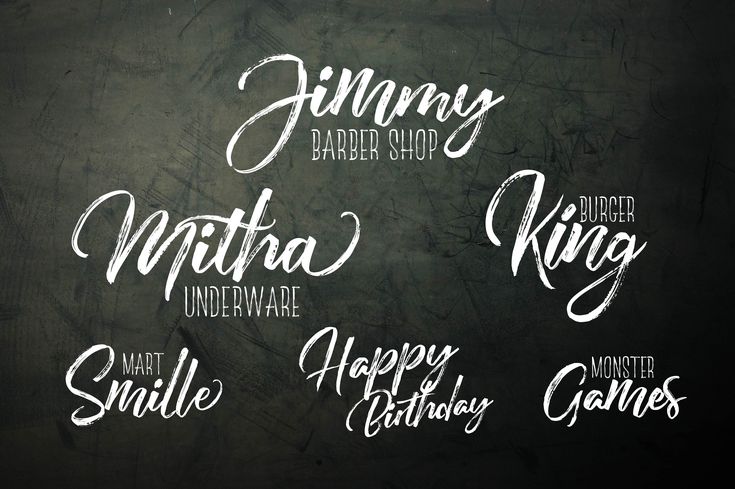
Подборка бесплатных русских рукописных шрифтов — Таня Захар на vc.ru
1. Шрифт Celestina скачать бесплатно
Отличный рукописный шрифт, он кажется довольно веселым и игривым, эта эмоция выражается благодаря разной высоте построения букв. Длинный текст читается довольно трудно, поэтому не используйте celestina шрифт кириллица в больших объёмах.Скачать шрифт Сelestina
2. Шрифт Brush font one скачать бесплатно
Бесплатный рукописный шрифт — Brush Font One созданный от руки и относится к классу шрифтов без засечек. Поддерживает латиницу и кириллицу. Довольно выразительный шрифт с угловатыми буквами. Подойдет на те случаи, когда нужно создать эффект написанного вручную. В целом — очень даже красивый шрифт для текста. Подходит для личного и коммерческого использования.Скачать шрифт Brush font one
3. Шрифт Elowen скачать бесплатно
Нежный, мягкий каллиграфических шрифт с толстой кистью .
Подойдет для рекламных компаний детских или женских брендов. Elowen Caps — Ваш отличный компаньон в тех случаях, когда нужен яркий заголовок. Поддерживает латиницу и кириллицу.Elowen русский шрифт скачать
4. Шрифт березки скачать бесплатно
Еще один легендарный шрифт от Миши Панфилова. Шрифт березки выделяется на фоне остальных благодаря вытянутым буквам, «нацарапанные» с легкой небрежностью и задиристостью, подойдут неформальному бизнесу — как на вывеске, так и в вебе. Настойчиво рекомендуем добавить его в свою рабочую папочку «шрифты для фотошопа». Поддерживает кириллицу. Березки шрифт скачать
5. Шрифт Tangak скачать бесплатно
В данном топе представлен шрифт «Tangak» не зря! Неформальный и уникальный шрифт для айдентики кафе и бара. Заголовка в книгах и прочей полиграфии. Шрифт поддерживает латиницу, кириллицу, цифры, знаки препинания и пунктуации, прописные и строчные буквы. Шрифт «Tangak» Вы можете скачать бесплатно в форматах EOT, OTF, SVG, TTF, WOFF, WOFF2.
6. Шрифт Gvozdi скачать бесплатно
Gvozdi шрифт — смотрится забавно на этой картинке, но автор не имел и другой посыл: если применять рукописный шрифт Гвозди в образовательных или художественных текстах, к примеру, о войне, читатели заметят эту небывалую «злость» и «агрессию». Наша редакция часто его использует в своих проектах и считает, что это очень красивый русский шрифт.Скачать рукописный шрифт Гвозди
7. Шрифт Kurica Lapoi скачать бесплатно
Тут-то и название красноречивое, говорит само за себя: корявый, как бы небрежный «Курица лапой» добавит юмора в ваш дизайн. Если не боитесь смеяться над собой, скачайте этот шрифт.Kurica Lapoi шрифт
8. Шрифт lemon tuesday скачать бесплатно
«Лимонный вторник» яркий и неординарный шрифт, его можно поставить в заголовке меню летнего кафе — он подчеркнет непринужденность и легкость обстановки. Но помните, что хотя скачущие буквы выглядят современно, использовать их нужно в малом количестве (утомляет читателя).
9. Шрифт Kobzar KS скачать бесплатно
Еще один довольно «нервный» и «небрежный» шрифт, который в полной мере имитирует письмо на скорую руку. Подойдет, когда нужно создать ощущение личного общения и подчеркнуть стиль.
10. Шрифт Masquerouge скачать бесплатно
Красивый рукописный шрифт с вытянутыми буквами, создает динамику и ощущение современного начертания. А вот очертания, которые отсылают к славянской письменности, создают брутальное настроение. Попробуйте оформить с помощью Masquerouge модные товары для мужчин и брутальных брендов. Используйте этот красивый рукописный русский шрифт совершенно бесплатно в своих проектах! поддерживает латиницу и кириллицу.Скачать шрифт Masquerouge